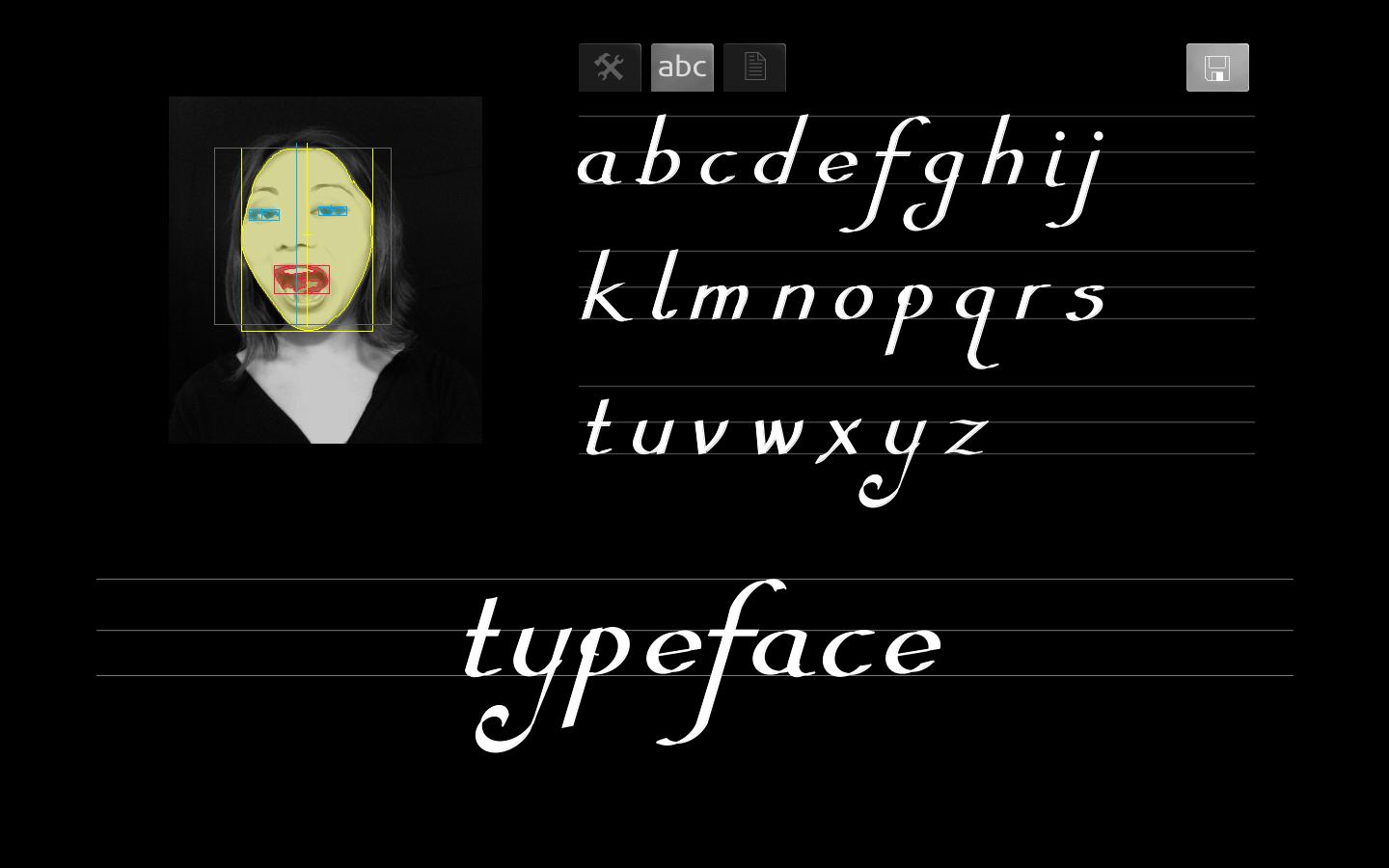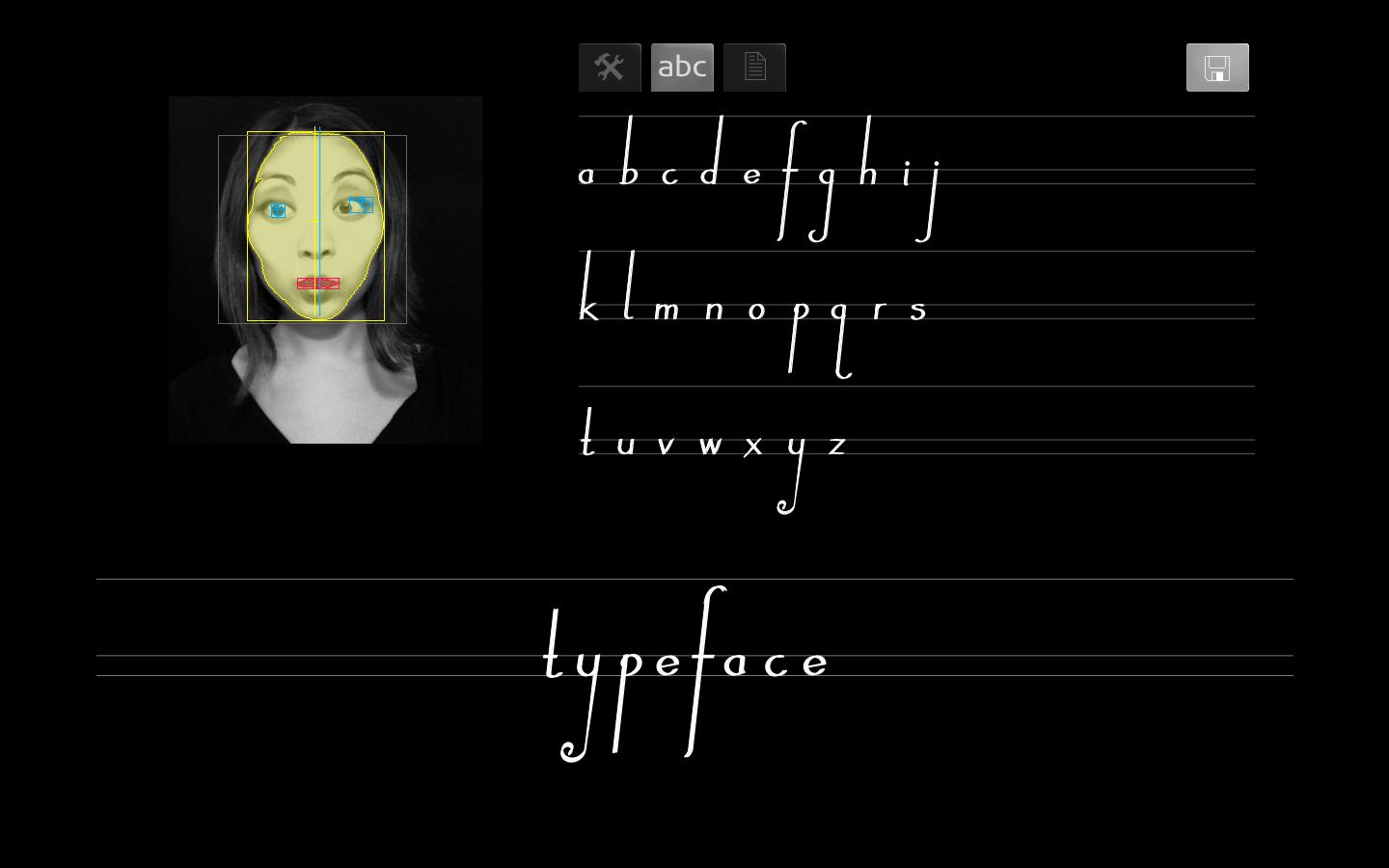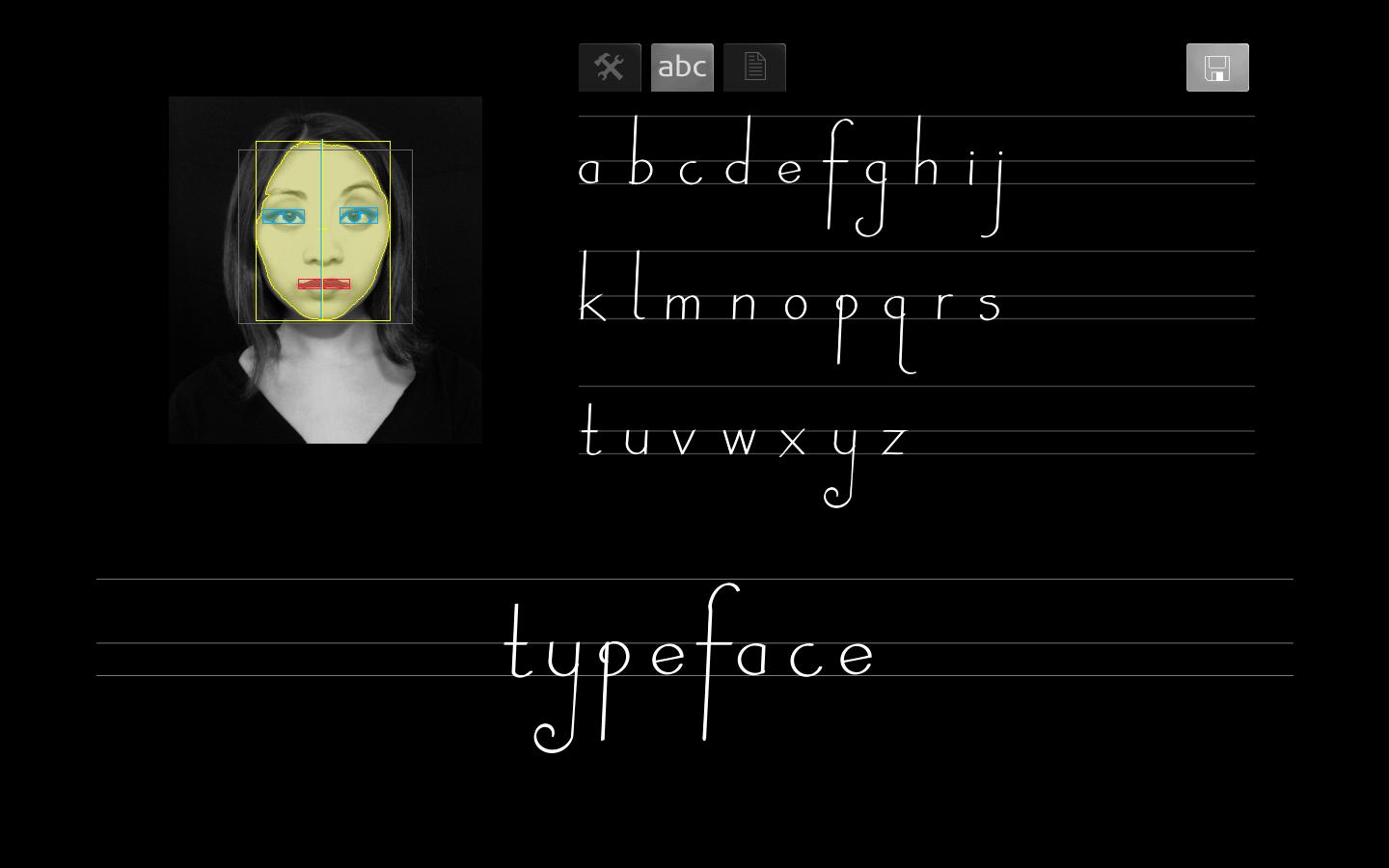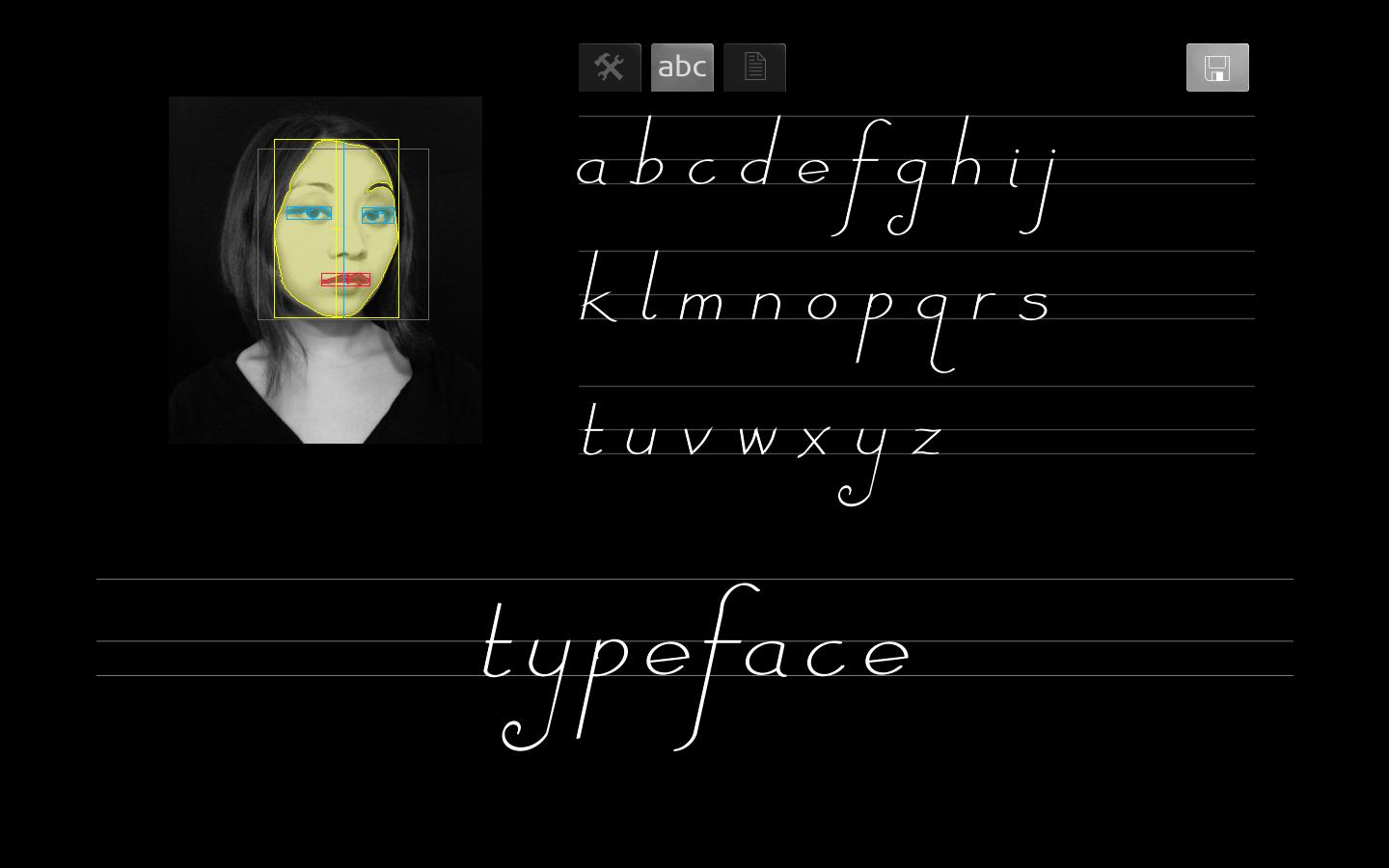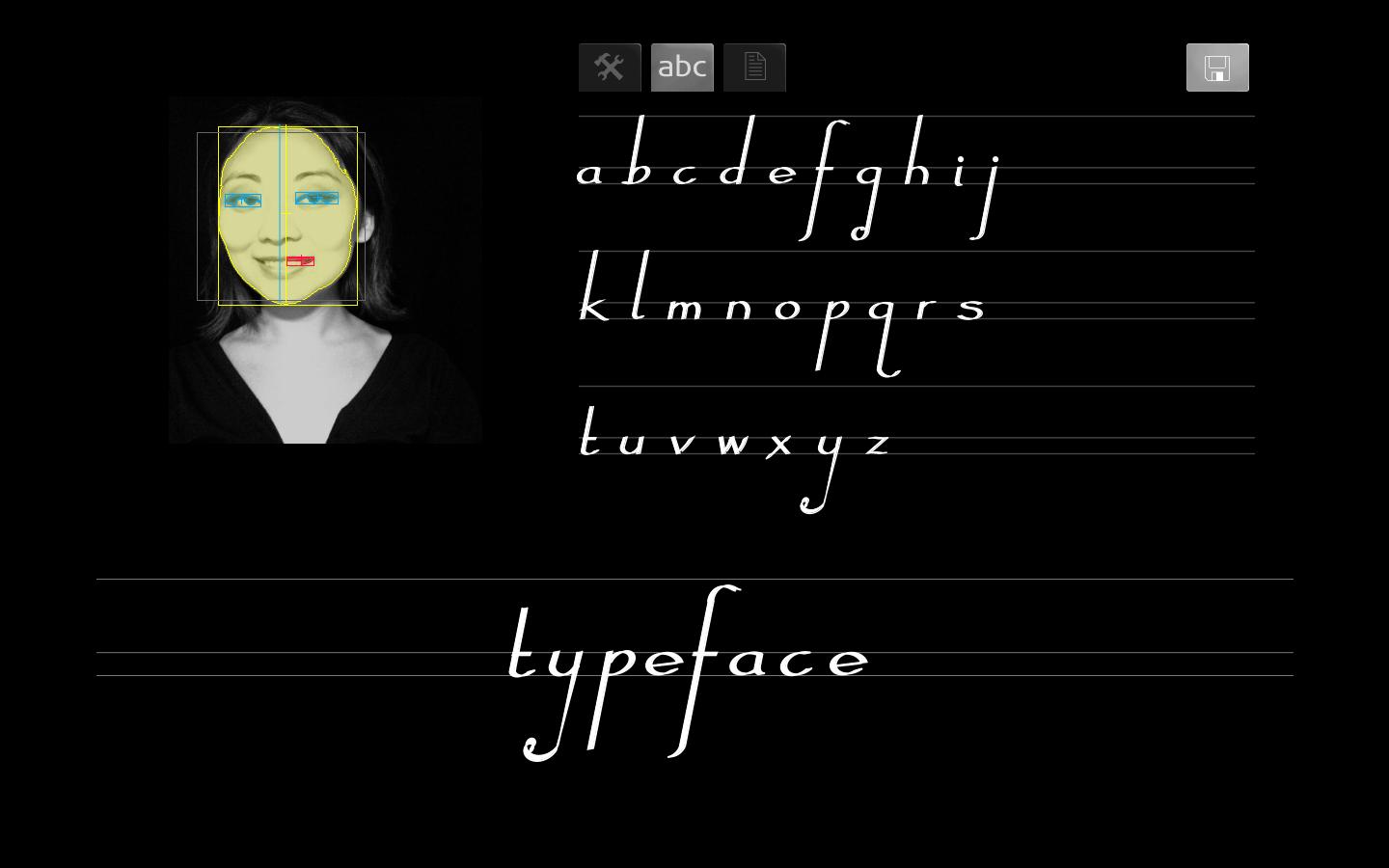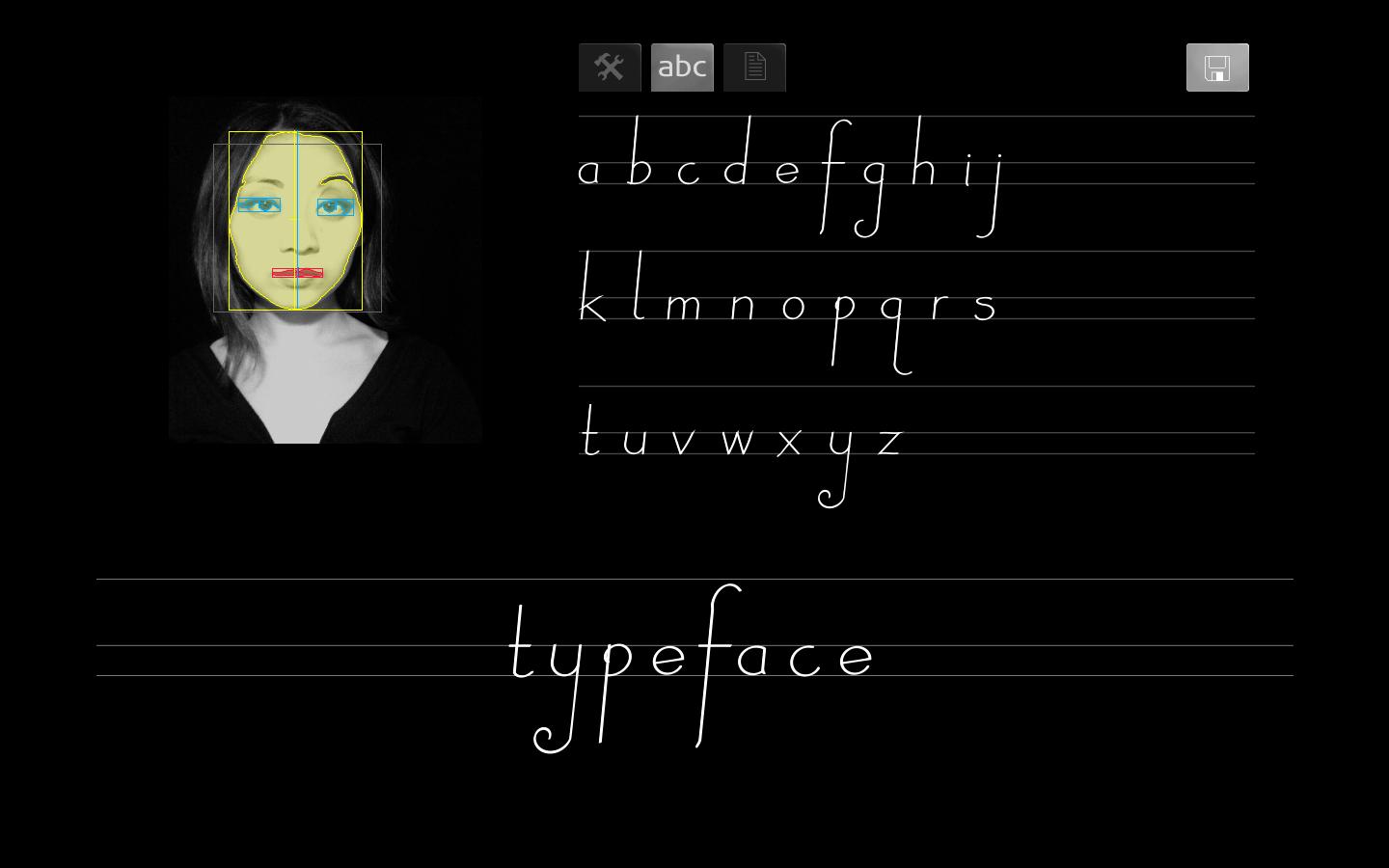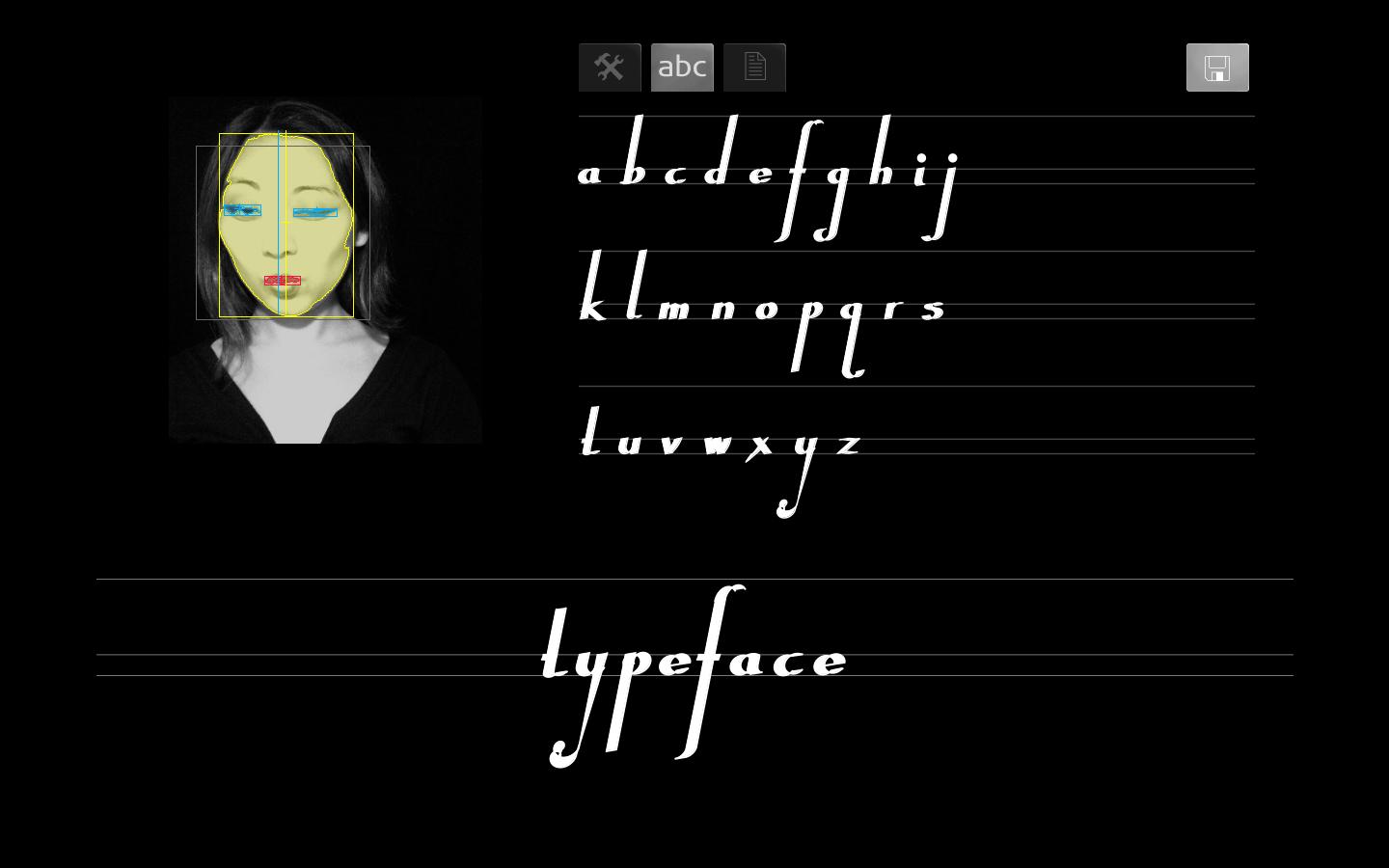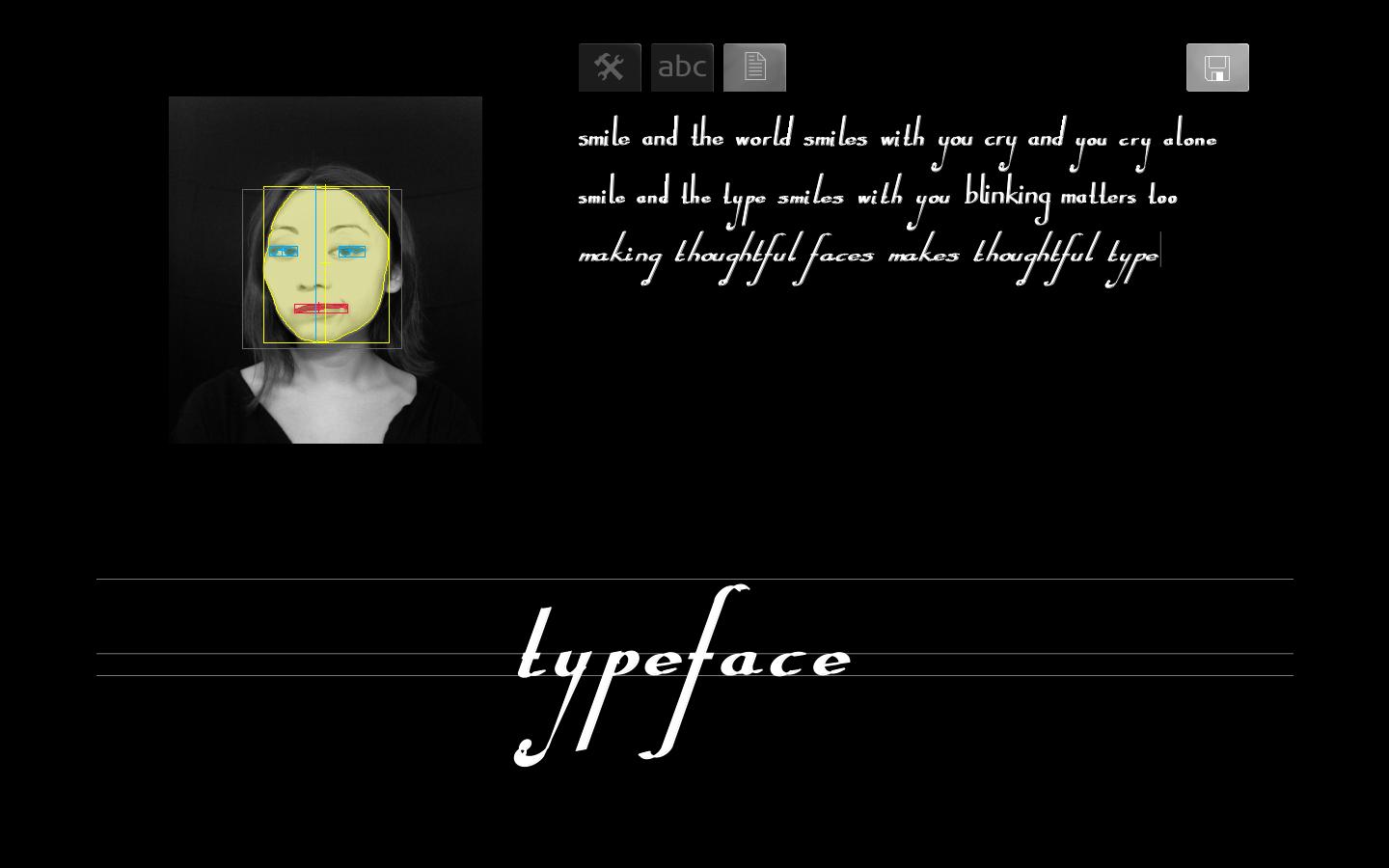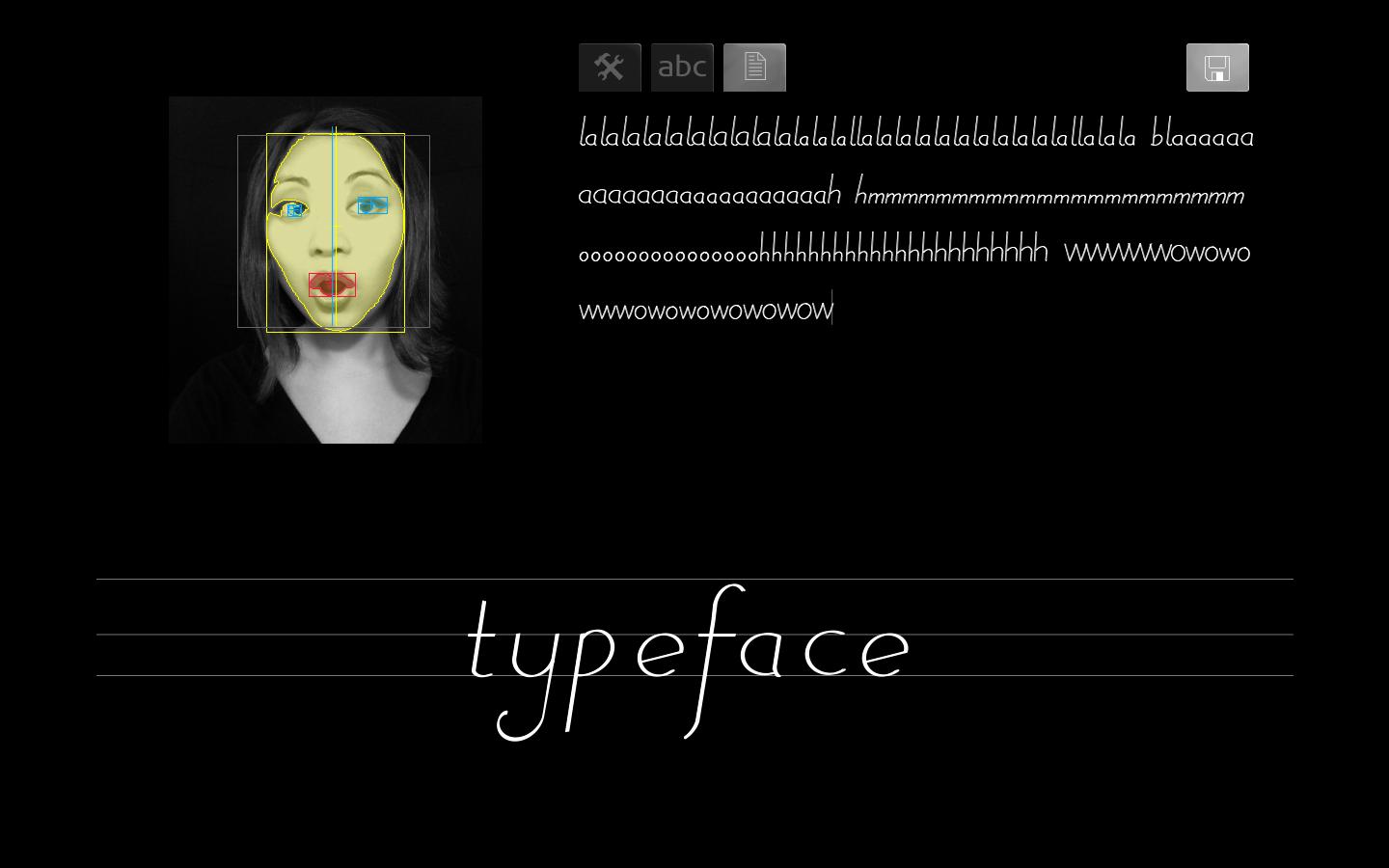
Mary Huang, 2011
Typeface Project es un sistema que vincula el reconocimiento facial con la tipografía interactiva. El software captura gestos espontáneos del usuario, como una sonrisa, y los traduce en modificaciones dinámicas de los tipos en tiempo real.
Su principal aportación es la exploración de la personalización tipográfica a través de un input biométrico. El proyecto evidencia de forma explícita la tensión que se produce entre la innovación formal, impulsada por la interacción, y la legibilidad tradicional del glifo.
La relevancia para esta investigación es que se trata de un referente temprano de la intersección entre la visión por computador y el diseño tipográfico interactivo.
- Década: Década de 2010
- Función: Exploración formal y/o performativa
- Contexto: Investigación / Experimental
- Grado de interactividad: Interacción débil o reactiva
- Input multimodal: No
- Tipo de input: Gestual
- Tipo de output: Transformación morfológica
- Tecnología empleada: Processing, OpenCV
- Alfanumérica: Sí
- Mantiene codificación textual: No